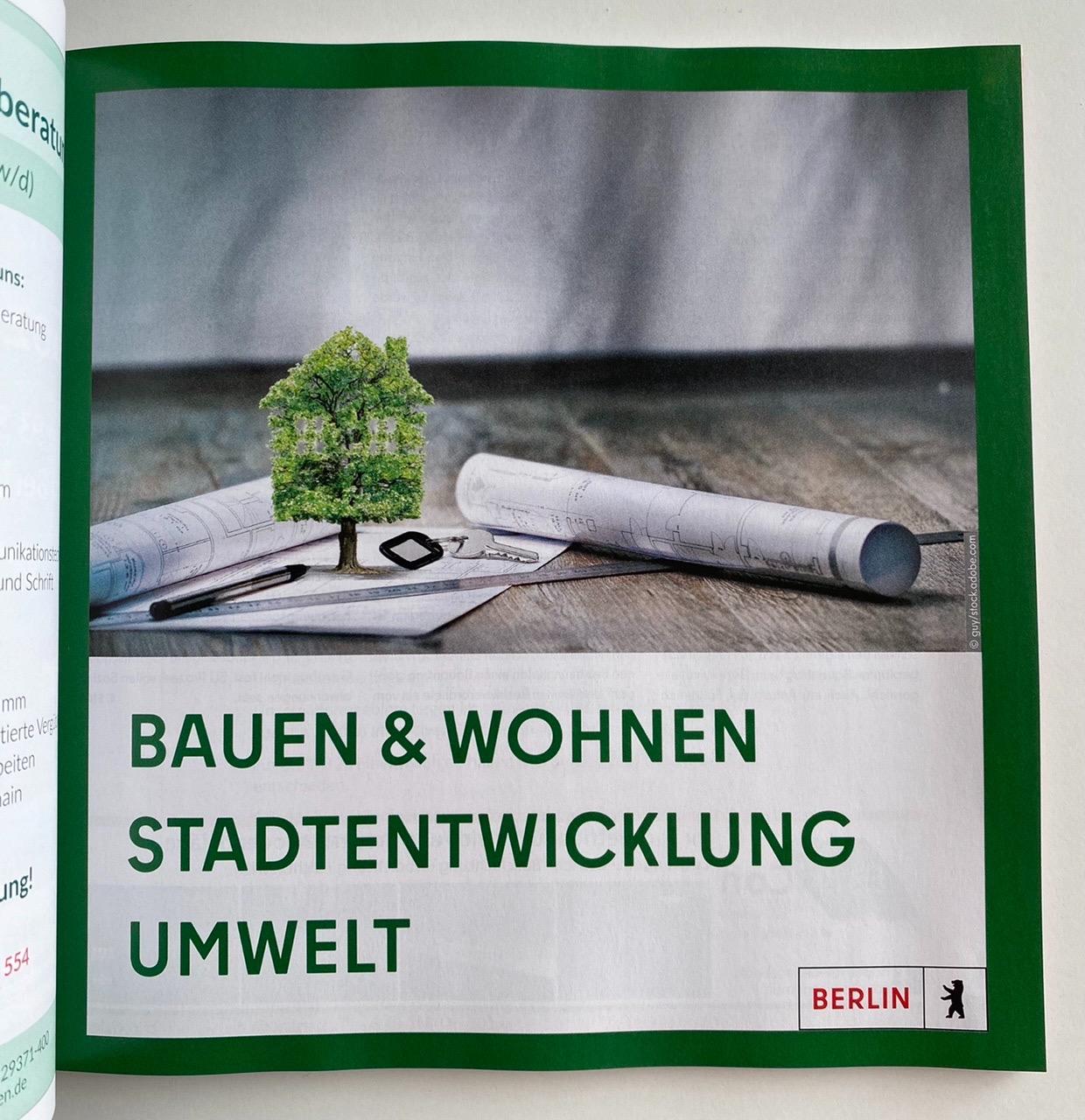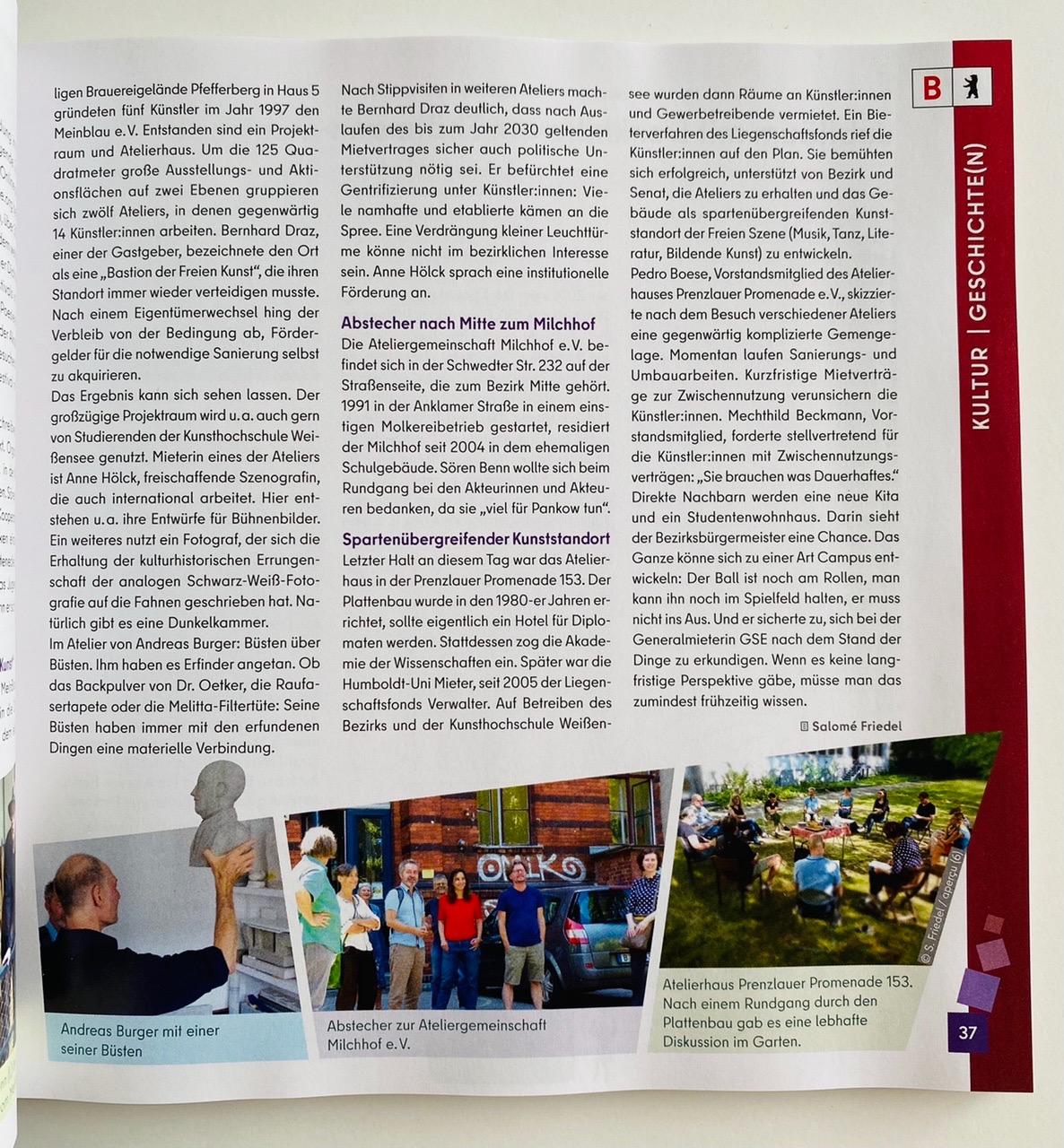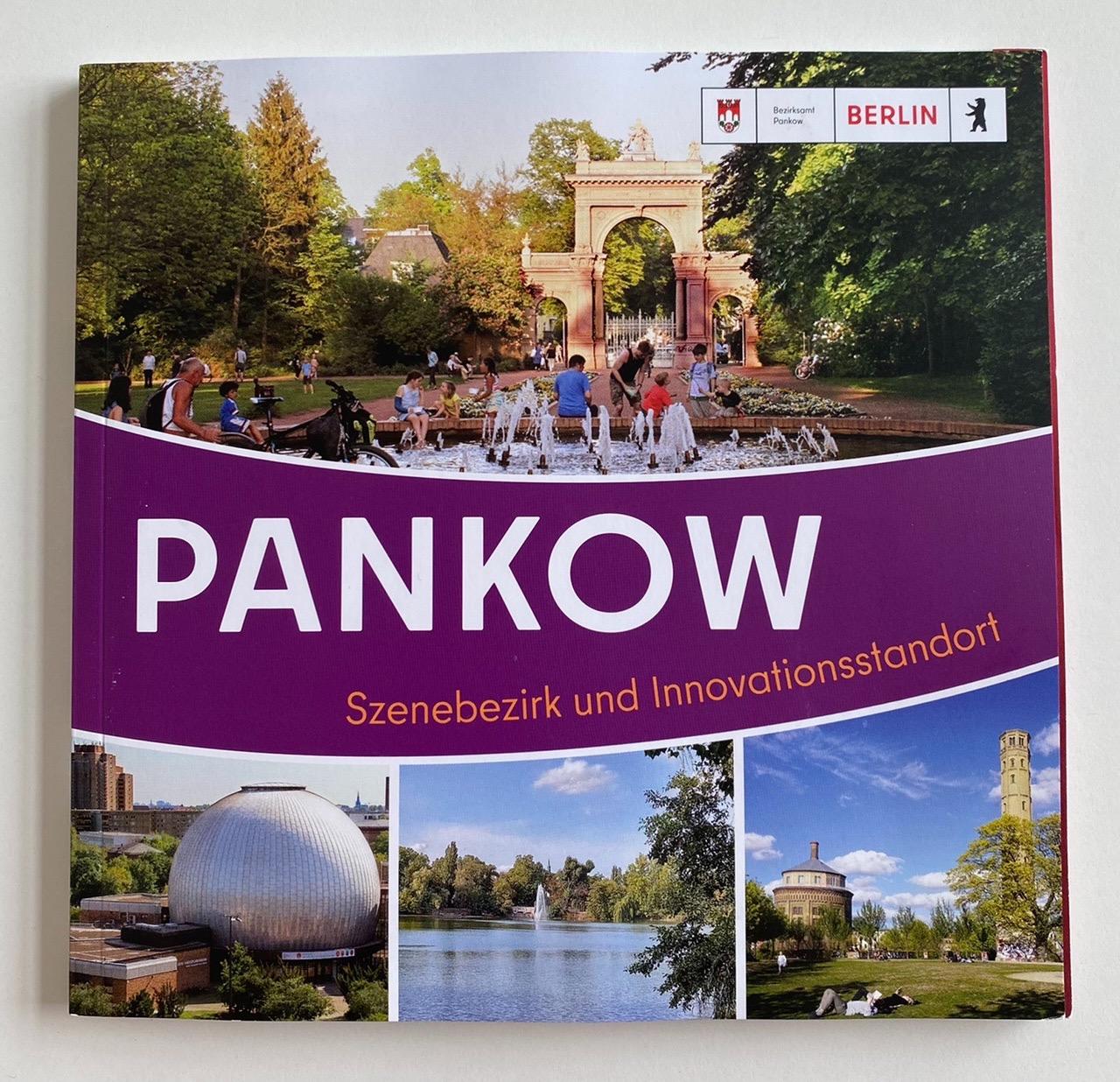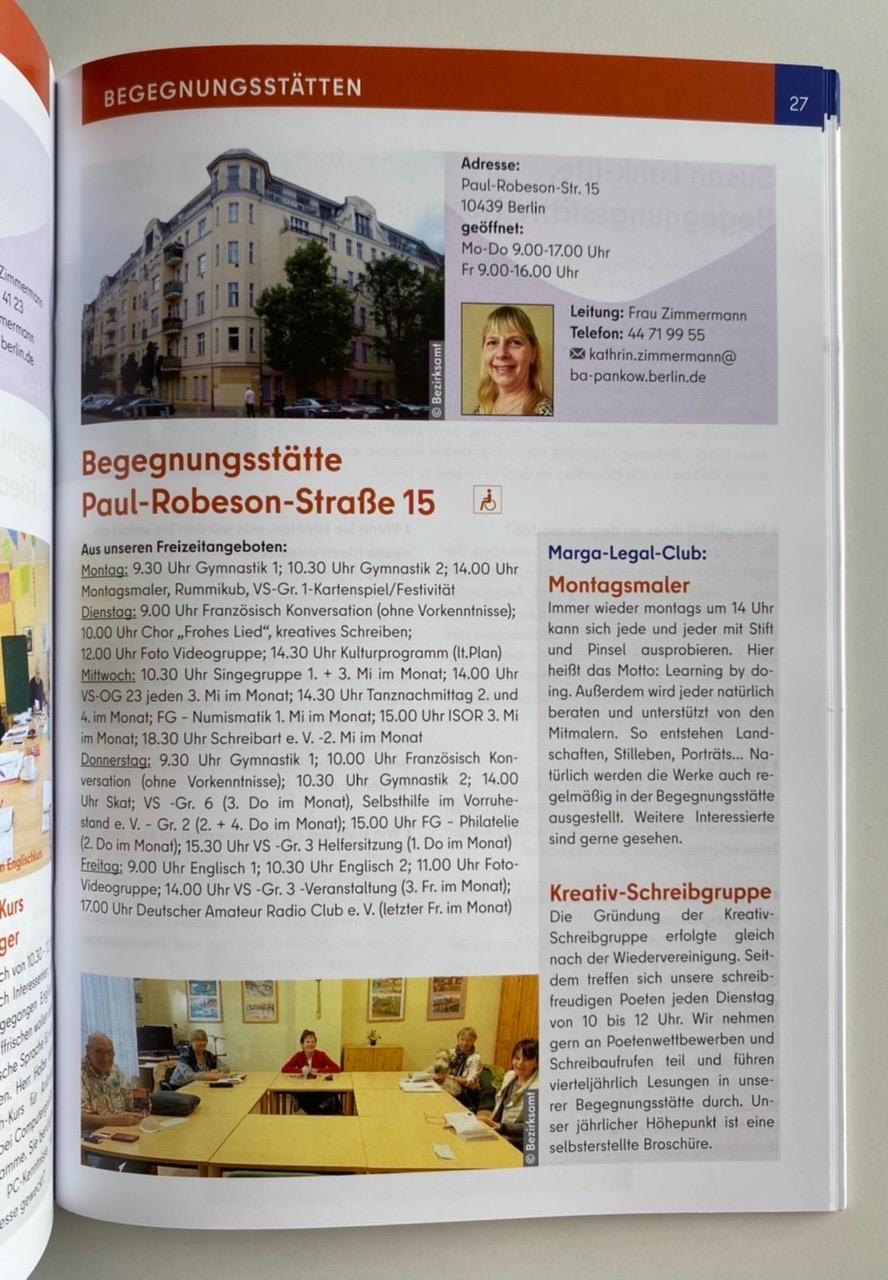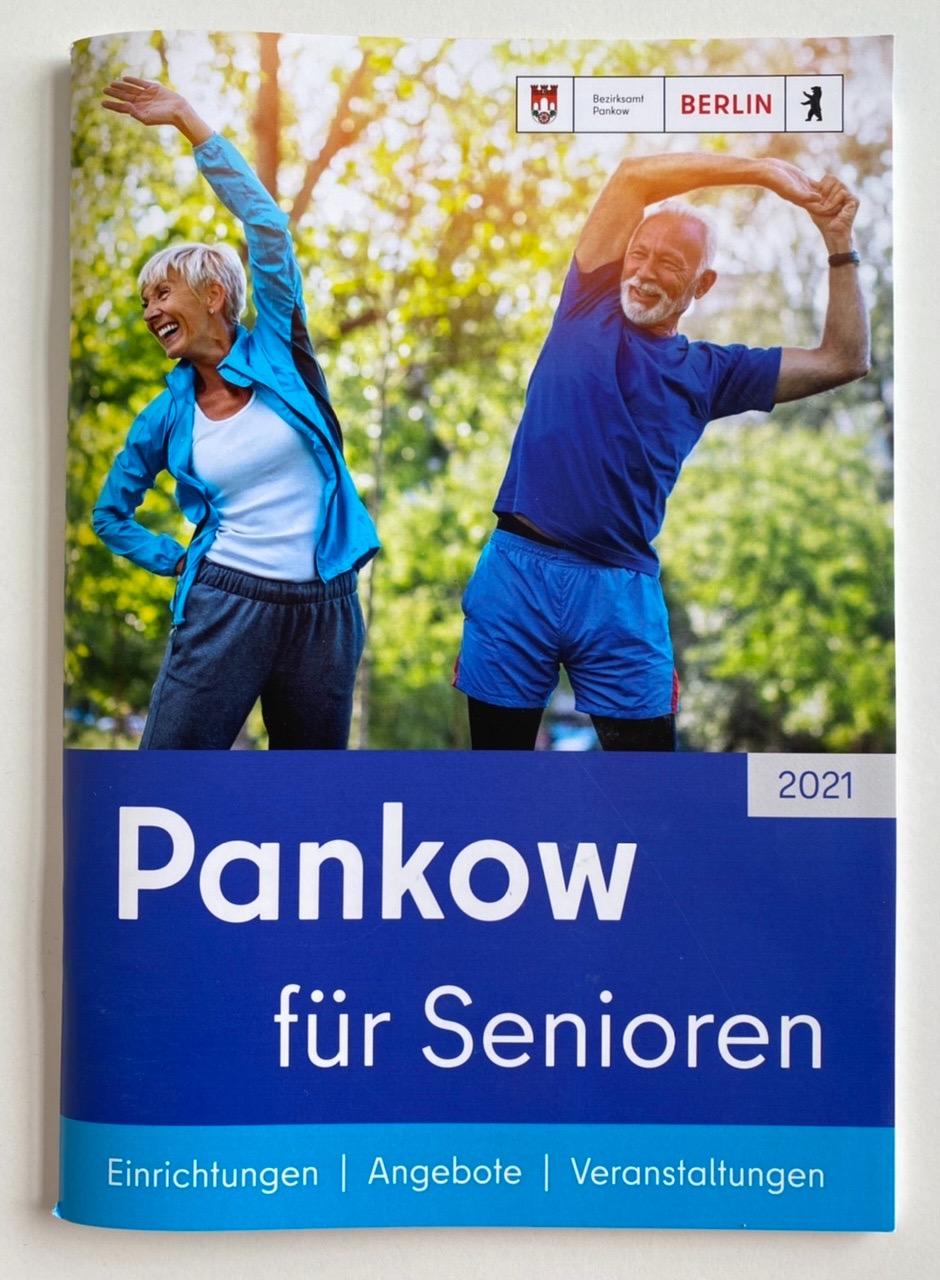
Berlin Corporate-Font
die Stadt Berlin hat ja ein neues Erscheinungsbild und damit eine neue Custom Hausschrift: "Berlin Type" von Hannes von Döhren.
Ich finde dieses neue Corporate Design, das sich wohl etwas retro-mäßig an die 60er-80er Jahre anlehnt, etwas muffig.
Die Schrift ist natürlich interessant. Ich bekomme jetzt allerdings mit ihr gesetze Behörden-Schreiben, wo sie nicht in Vektoren dargestellt wird, sondern pixeligen Bitmaps. Zuvor waren diese Schreiben in Calibri und m.M. besser lesbar. (Vielleicht verwenden die Autoren dieser Schreiben nicht die Office-Version der Schrift.)
Was ist eure Meinung zur Berlin Type?
Mir gefällt die Schrift ganz gut, erinnert etwas an die Fibel-Schrift hat aber auch dieses Retro-Feeling. Ob das für Berlin passt, keine Ahnung – vom Zeitgeist her schon. Längerfristig finde ich es aber schade das man sich von dem alten CD verabschiedet hat, das hat für mich gut funktioniert. (also das von MetaDesign – die Erweiterung mit dem be fand ich dann nicht mehr so toll). Das Signet des Tors in positiv/negativ und als Zeichen der Wiedervereinigung  wirkte im Gegensatz zum jetzigen Design zeitlos.
Die Schrift finde ich auch durchaus interessant, ich weiß nur nicht, ob diese Retro-Optik so eine gute Idee ist. Ich denke dabei irgendwie an verqualmte U-Bahnen der 70er Jahre mit David-Bowie-Plakat und Christiane F. auf Heroin ... Erinnert mich auch irgendwie nur an West-Berlin samt Mauer und nicht ans vereinte Berlin der Jetzt-Zeit. Da hat mir das bisherige CD auch besser gefallen und vor allem besser gepasst.
Als Bürger dieser hoffnungslos im Verwaltungschaos liegenden Bankrott-Stadt hoffe ich jedenfalls, dass man am neuen CD lange festhält, und nicht in 10 Jahren schon wieder eine ordentliche Summe für einen neuen Markenauftritt ausgibt.
Was genau meint ihr mit Retro? Ich finde die Schrift eigentlich recht klassisch wenn man von einigen Hipster-Elementen absieht …
Die geben ja selbst an, sich an Berlins Straßen- und U-Bahn-Beschilderungen der 20er Jahre zu orientieren bei der Schrift.
Gut, die ist ja nur ein Bestandteil des CDs, aber die Aufmachung und die Farben des Erscheinungsbildes hat ja schon eher Retro-Charakter, meiner Meinung. (Abgesehen von den gewollt-lustigen Sprüchen in den Kampagnen.)
Über die Kampagne kann ich wenig sagen. Dazu müsste ich erst mal mehr sehen und auf mich wirken lassen. Den Bären (zumindest in der kleinen Wort-/Bildmarke im Internetauftritt) finde ich etwas rundgelutscht; sein Rücken hat einen Schwung, als würde er Frack tragen.
Die Schrift (zip-Datei) nimmt in den Versalien klassische Proportionen auf. Dass sie retro wirken könnte, liegt vielleicht an dem tiefen A-Strich und den großen Köpfen von P und R. Auch das Minuskel-t erinnert an das der Reichsbahn:
Was ich erstaunlich finde, ist die Reduzierung auf nur zwei Schriftschnitte (Regular und Bold). Auch wurden keine speziellen Schnitte für Displaygrößen (Opticals) angelegt. Von Variables ganz zu schweigen. Zusammen mit der einen Farbe (Rot plus Schwarz und Weiß) ist das schon sehr minimalistisch. Aber warum nicht? Kann man machen. Dass es trotzdem bunt und vielfältig werden kann, zeigt ja das Markenhandbuch (7z-Datei).
Die Schrift spricht lateinisch, griechisch, kyrillisch und verfügt über ein Versal-ẞ:
Sobald eine Schrift auf einem Drucker ausgegeben wird, gibt es keine Vektoren mehr, sondern nur noch Punkte. Früher kam es bei solchen Umstellungen oft zu Schwierigkeiten, wenn die alten Drucker-Gedächtnisse nicht mit dem neuen Font gefüttert worden waren. Das sollte aber heute längst Vergangenheit sein. Ich habe hier einen Probeausdruck gemacht; darauf wirkt die Schrift klar und leserlich. Vielleicht ist es eine Sache der Gewöhnung.
Die Verwaltung darf übrigens weiterhin ihre Bescheide in der Calibri (oder als Fallback: Arial) verfügen. So steht es im Markenhandbuch, S. 21.
Das oben verlinkte PDF kommt genauso vom Senat — die Punkte sind also im PDF.
Danke fürs Zeigen. Auch wenn die Schrift jetzt nicht »ganz vorne« ist, wirkt sie auf mich positiv emotional, irgendwie vertraut. Vielleicht ist das im Hinblick auf die unterschiedlichen Zielgruppen auch wichtiger. Mich stört einzig das Futura-t beim Lesen, aber das mag Geschmackssache sein.
Unabhängig von der Lesbarkeit drängt sich die alte Schrift deutlich mehr auf und hat quasi schon zu viel Charakter.